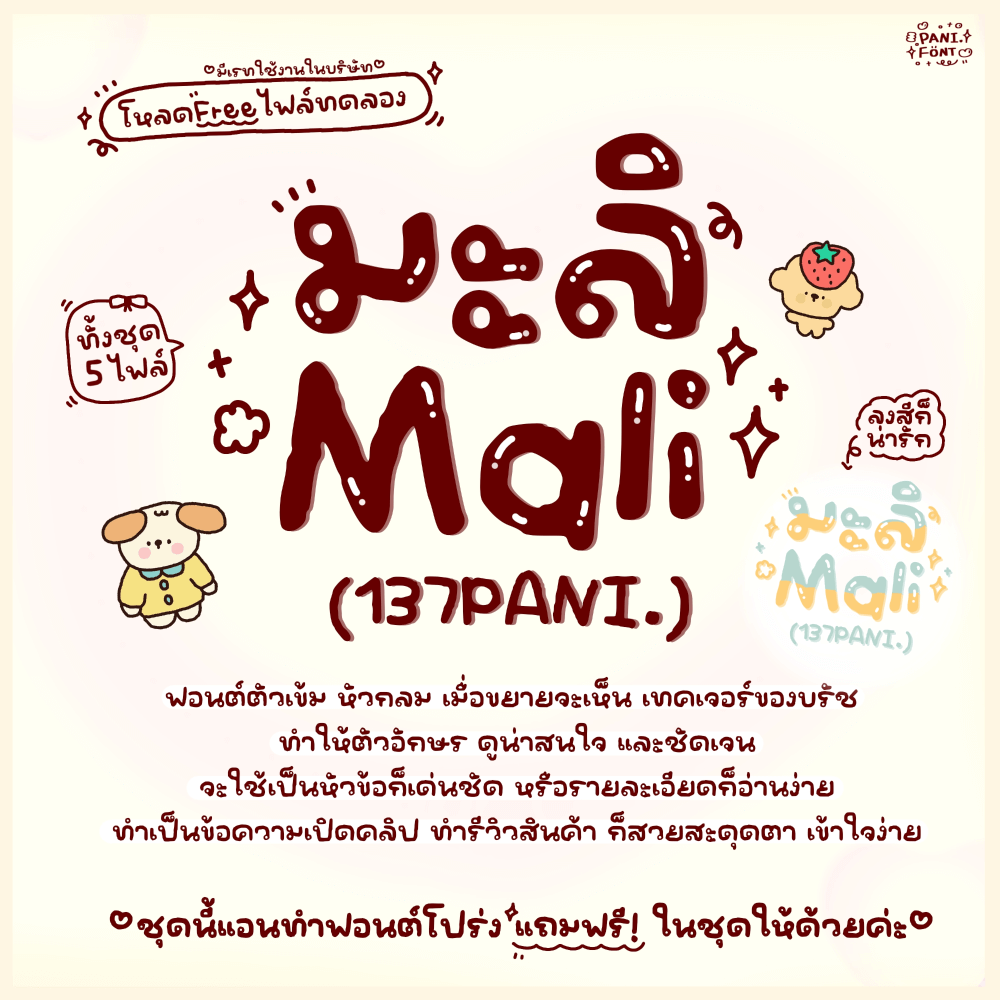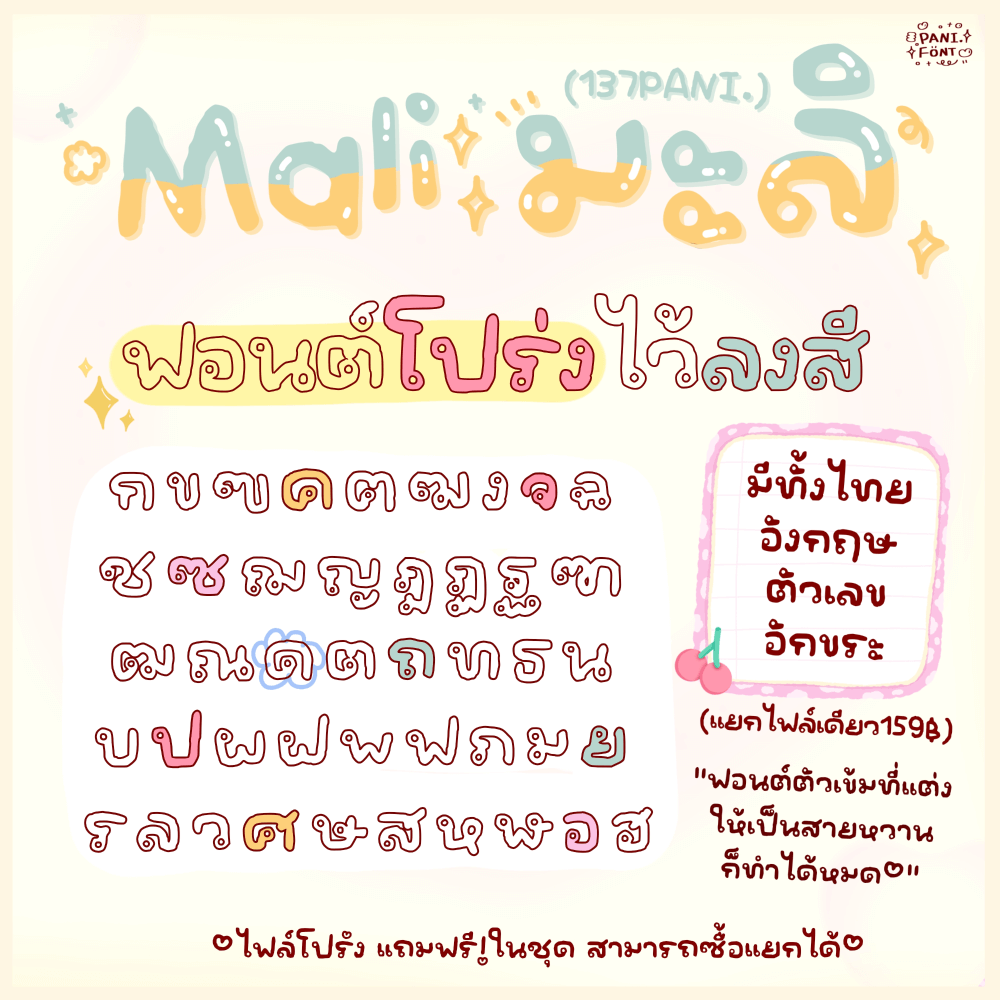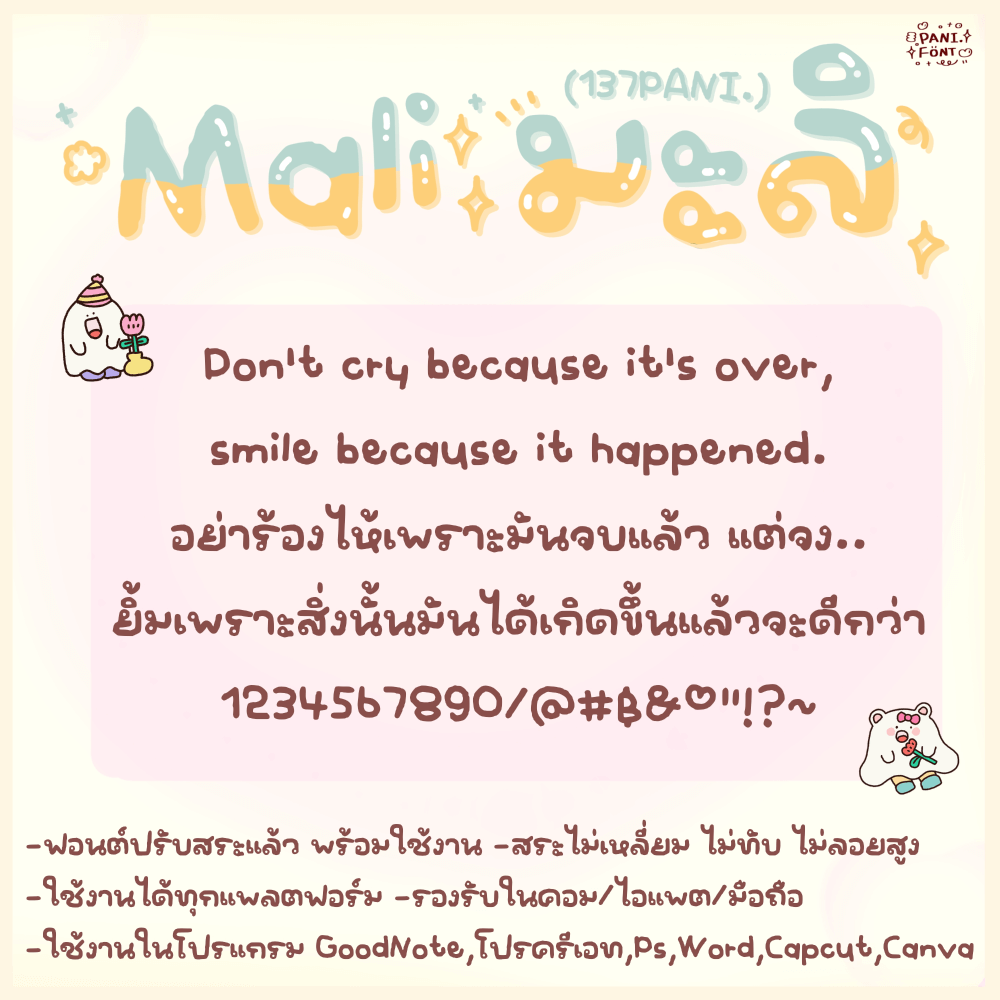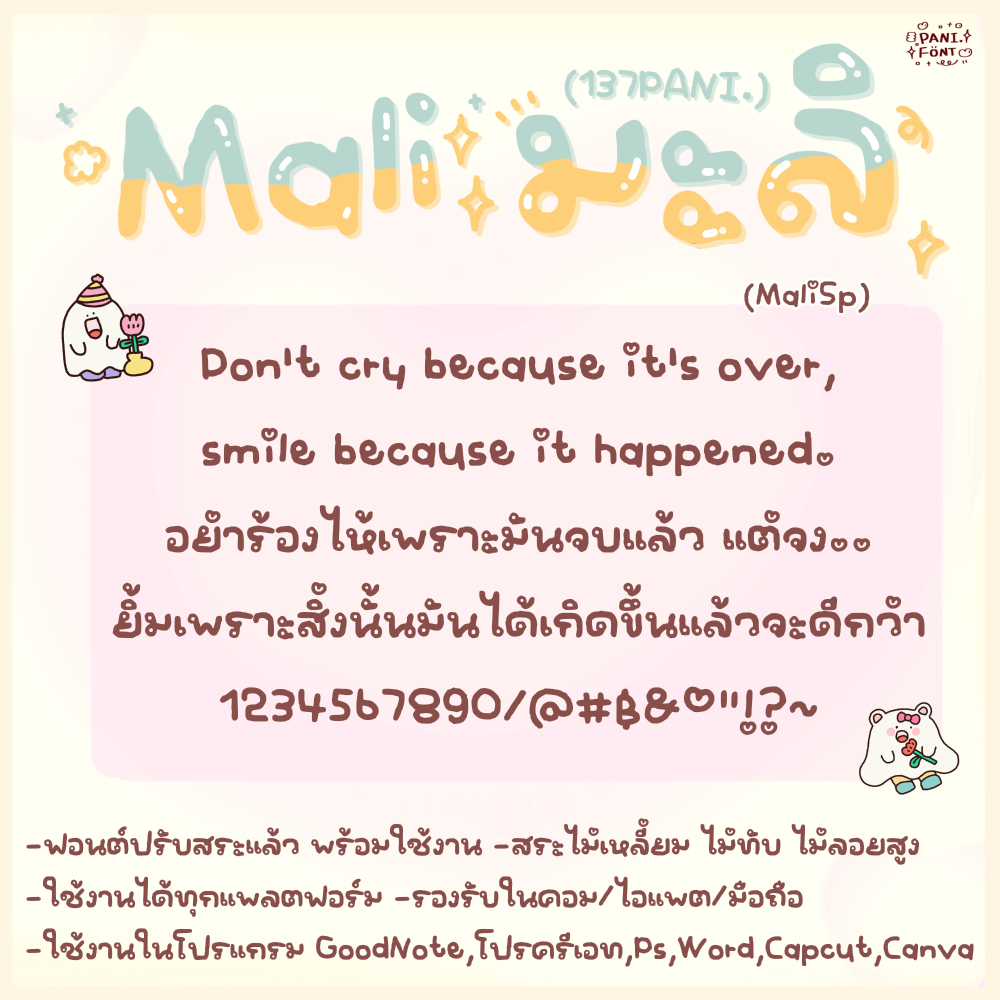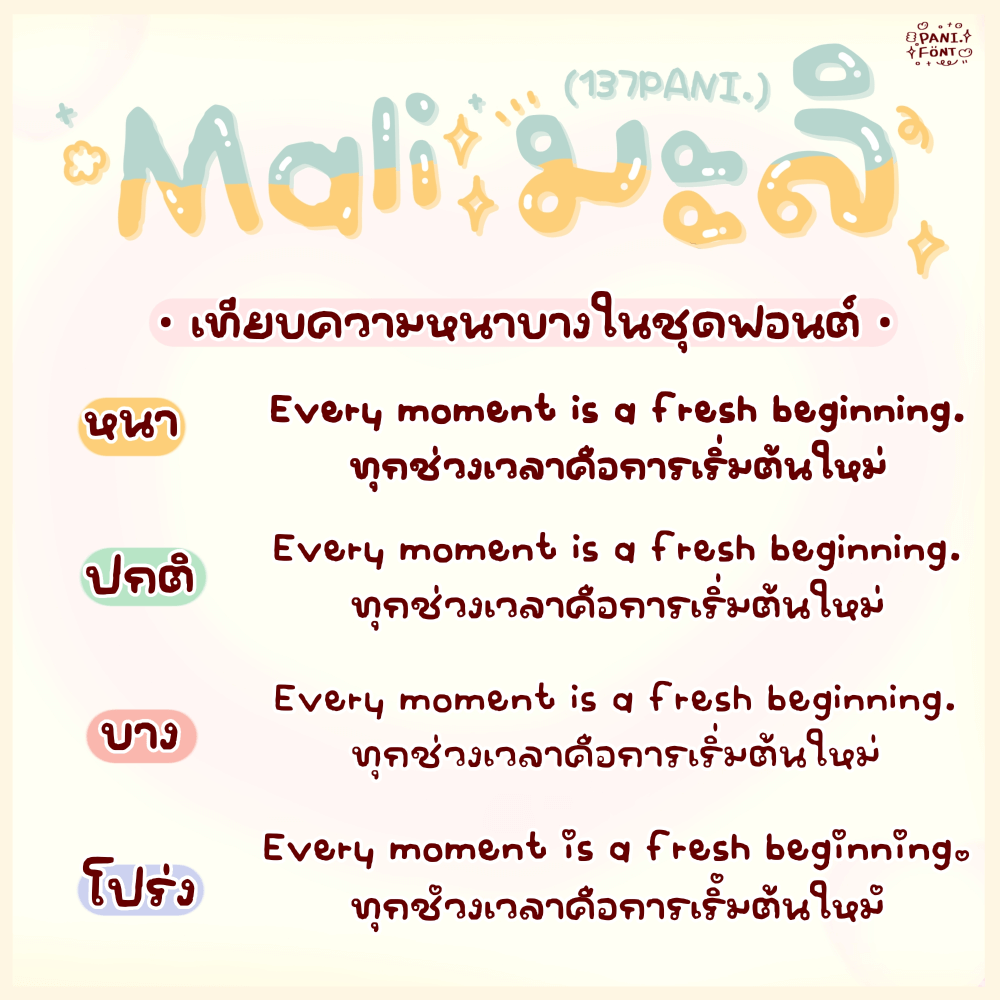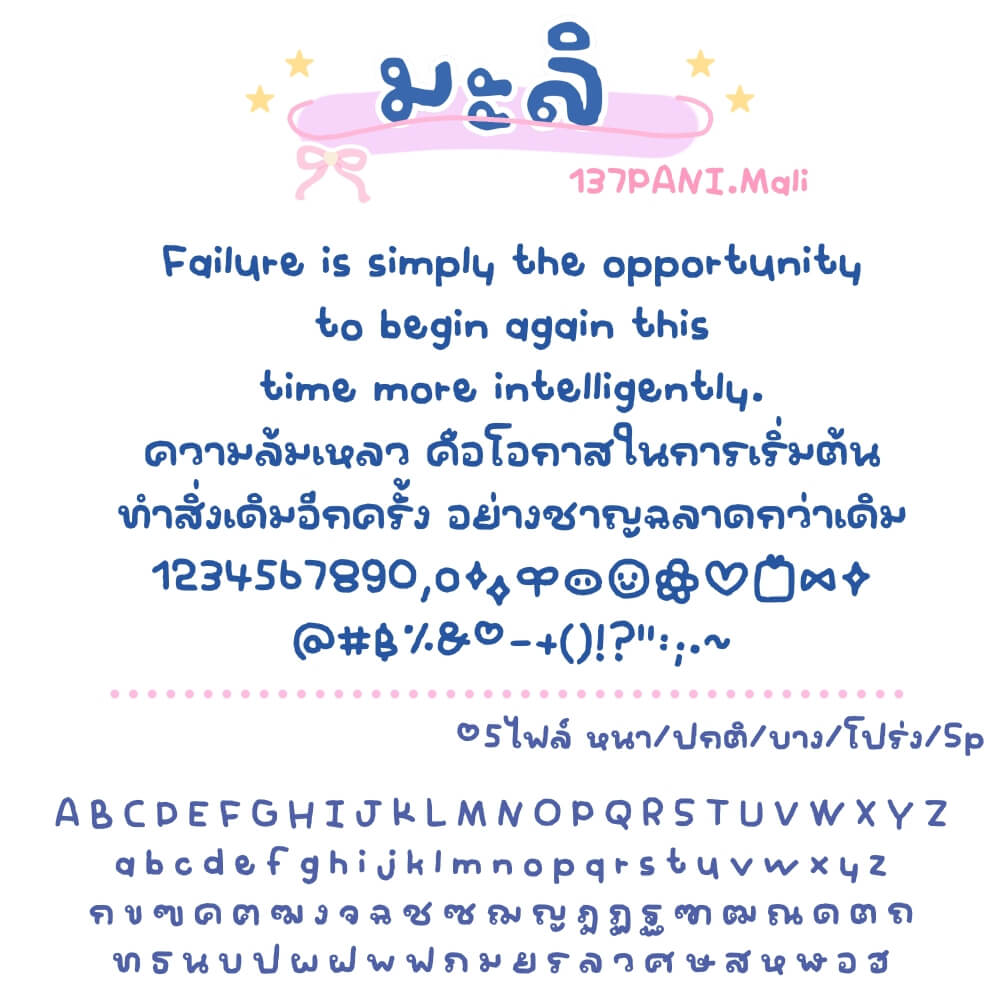
ฟอนต์ 137PANI.มะลิ – ฟอนต์ตัวเข้ม หัวกลม เมื่อขยายจะเห็น เท็กซ์เจอร์ของบรัช ทำให้ตัวอักษร ดูน่าสนใจ และชัดเจน
- เลขไทย เป็นตัวอีโมจิ
- ชุดนี้แอนทำฟอนต์โปร่ง แถมฟรี! ในชุดให้ด้วยค่ะ